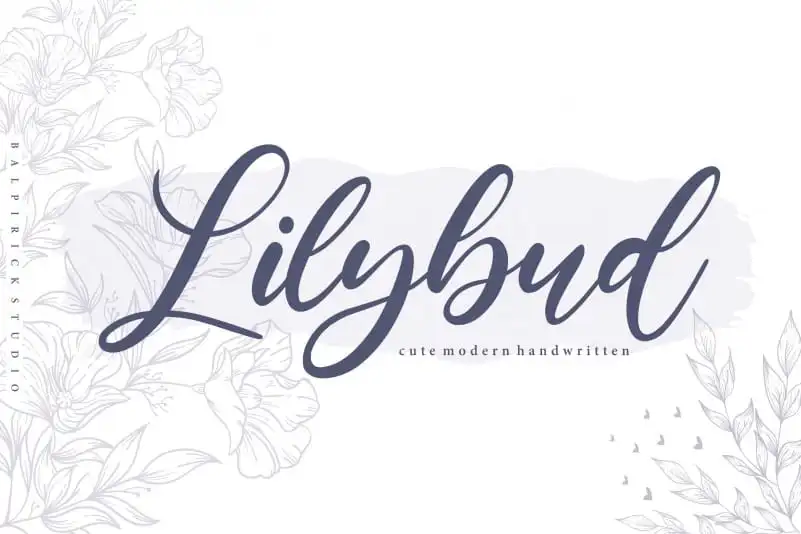
Lilybud Modern Handwritten Font – Download Grátis
A Lilybud Modern Handwritten Font é uma escolha perfeita para qualquer projeto que busque um toque delicado e elegante nas letras. Desenvolvida pelo designer balpirick, essa fonte moderna mantém a característica de escrita à mão que tanto conquista o público, permitindo transparência na expressão pessoal e emotiva das palavras. Suas linhas suaves e fluidas são perfeitas para aplicação em produtos de embalagem, identidades de marca, revistas ou até mesmo para criar um visual único nas redes sociais. Perfeito também para o mundo do amor, onde uma palavra delicada pode fazer toda a diferença no design de casamentos. Além disso, ela se destaca perfeitamente para expressar pensamentos e sentimentos acima de backgrounds mais sóbrios. Com Lilybud Modern Handwritten Font, você consegue entrelaçar o universo da escrita moderna com uma personalidade autêntica e vibrante. Quebre as regras e faça sua marca soar única e verdadeira com essa incrível fonte de balpirick.